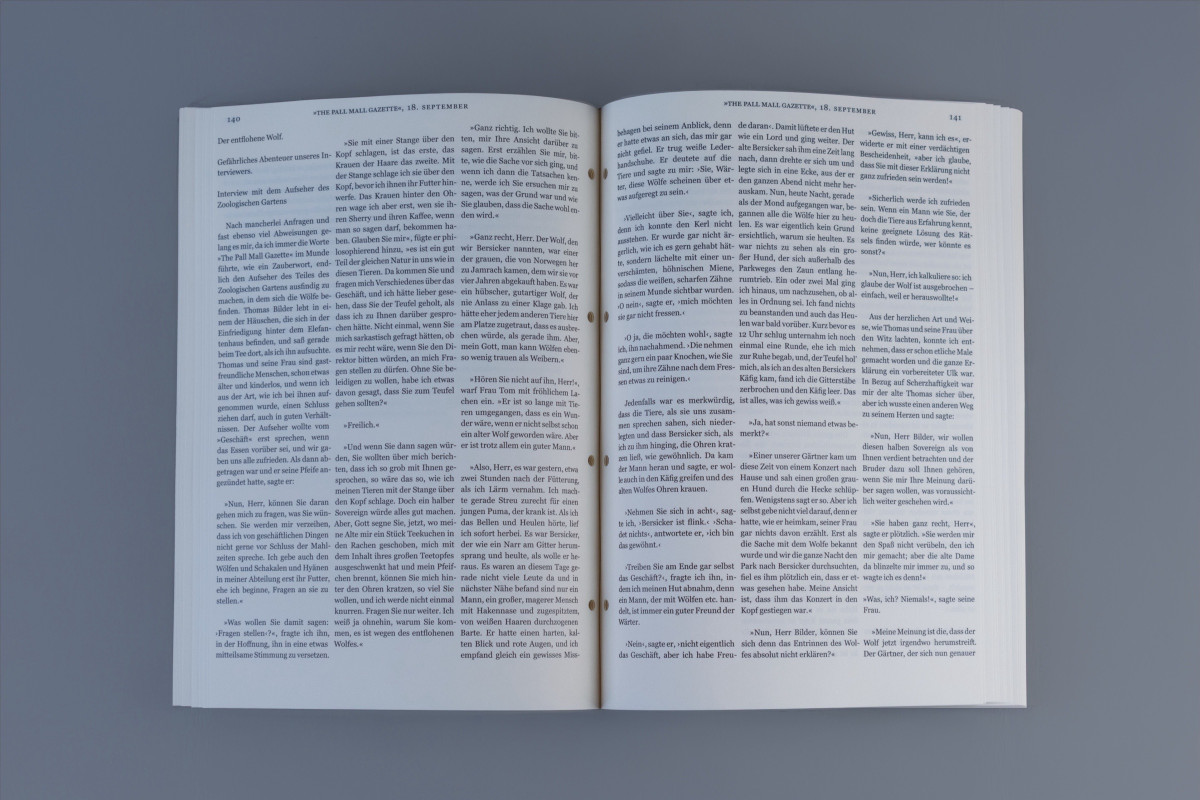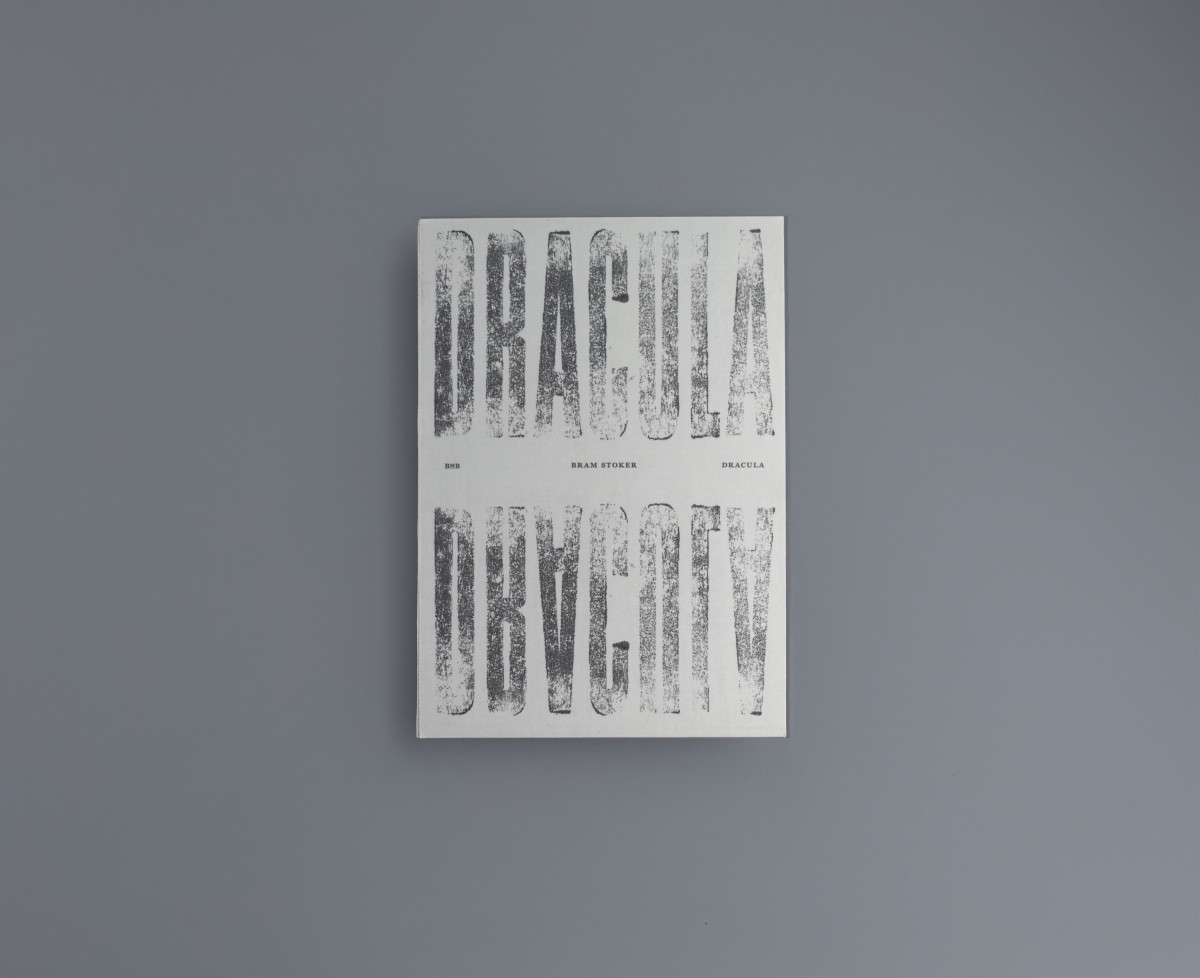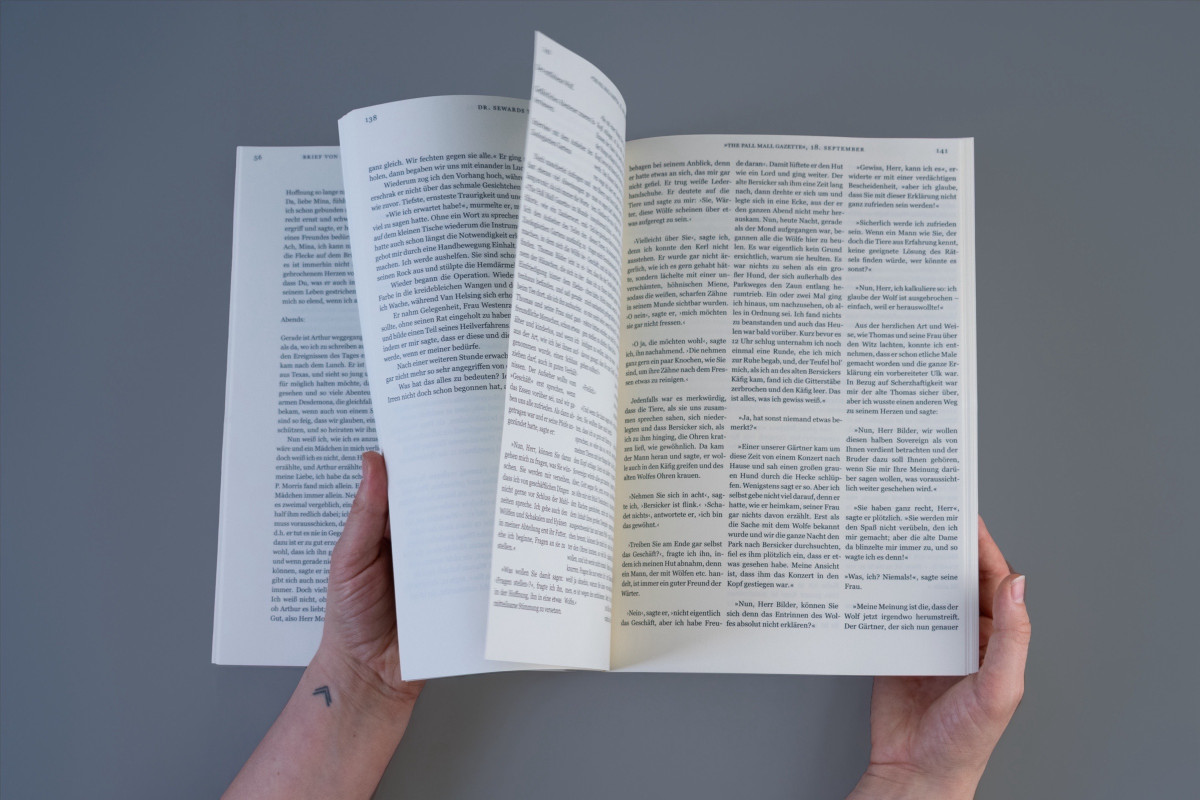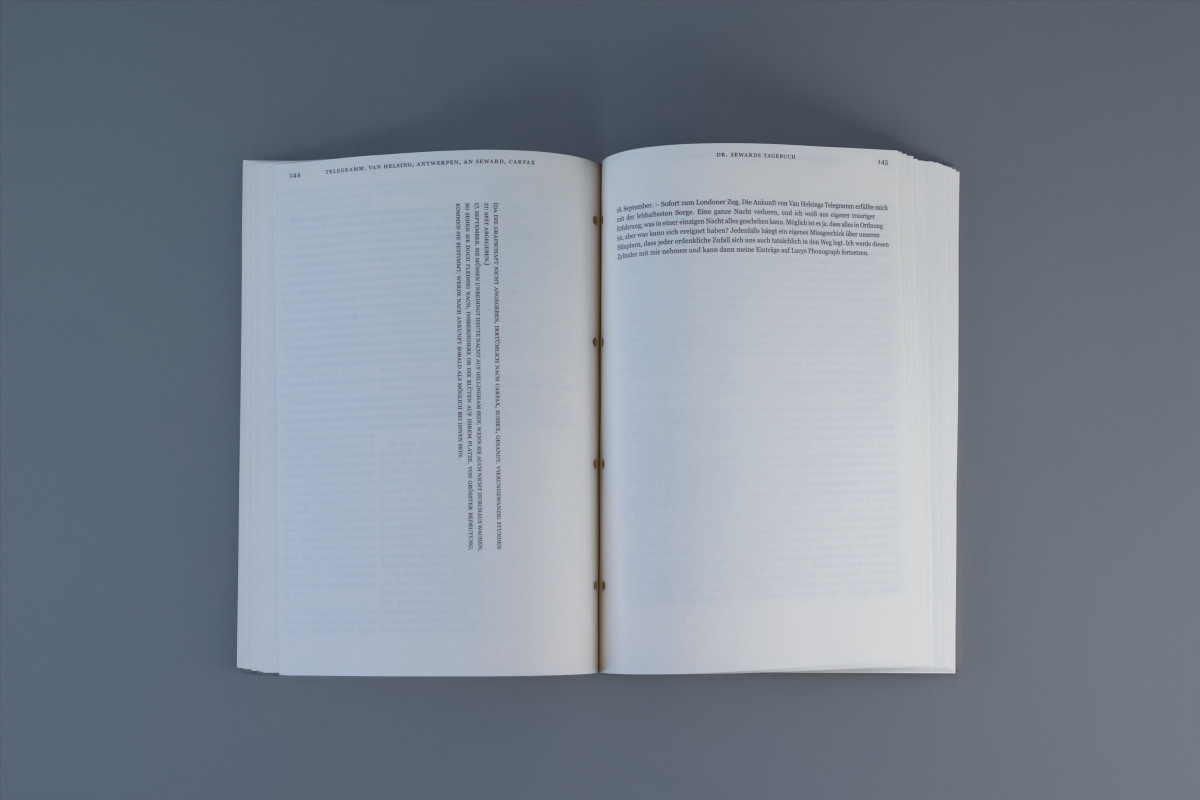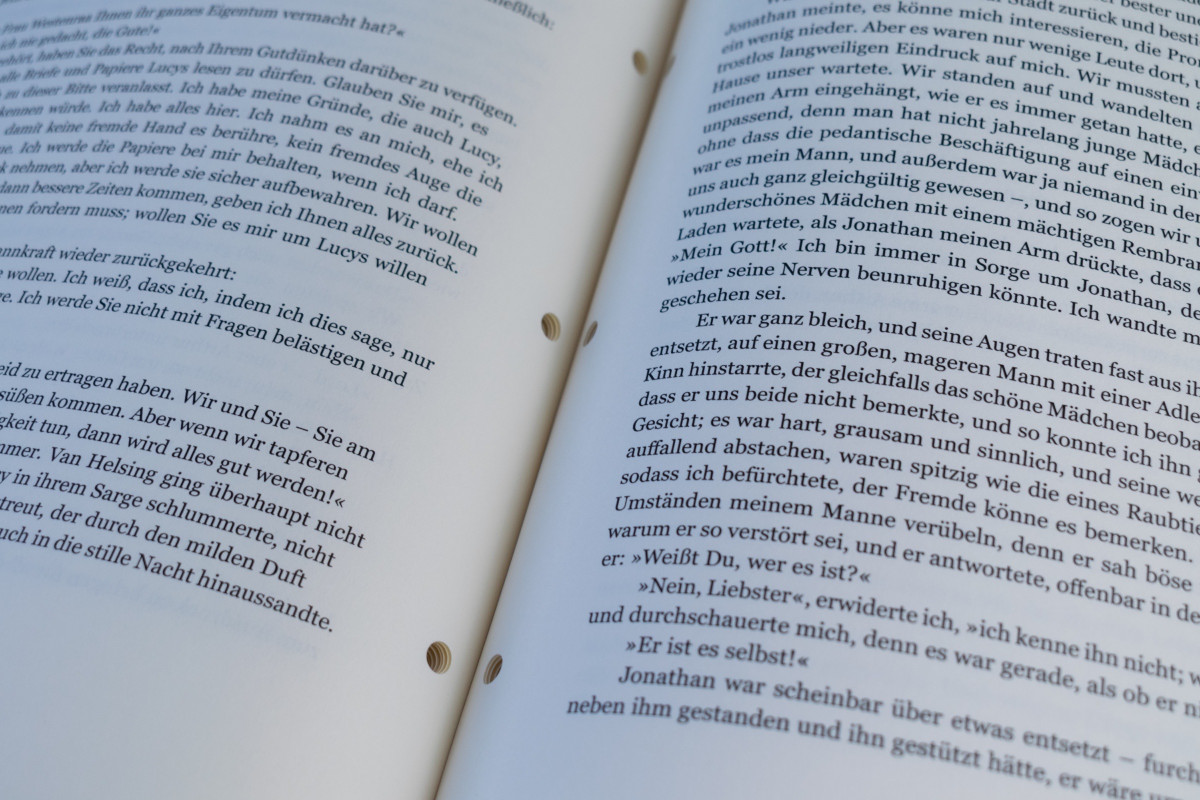
Mein Projekt „Dracula“ ist eine Buchgestaltung aus dem Sommersemester 2024.
Der Roman aus dem Jahr 1897 ist im epistolaren Stil geschrieben und besteht aus Tagebucheinträgen, Briefen, Zeitungsartikeln und anderen Dokumenten, die die Geschichte aus verschiedenen Perspektiven erzählen. Dieser Erzählstil ermöglicht es den Lesern, die Gedanken und Gefühle der Charaktere direkt mitzuerleben und schafft eine intime Verbindung zur Handlung.
Das Ergebnis meiner Arbeit war ein DIN-A4-großes Buch, das den Charakter einer Dokumentensammlung aufgreift. Ich entwickelte vier verschiedene Layouts für die unterschiedlichen Textarten, um den epistolaren Stil zu betonen. Die Dokumente wurden am Kopf des Buches bezeichnet und im Innenteil gelocht, was den Eindruck einer archivierten Akte erzeugt. Das Cover wurde mit silbernem Leinen bezogen und mit handgedruckten Bleisatzbuchstaben digital bedruckt. Das Buch erhielt einen offenen Rücken und eine Klebebindung.
My „Dracula“ project was a book design in which I reimagined Bram Stoker‘s novel.
The novel is written in epistolary style and consists of diary entries, letters, newspaper articles, and other documents that tell the story from various perspectives. This narrative style allows readers to directly experience the thoughts and feelings of the characters and creates an intimate connection to the plot.
The result of my work was an A4-sized book that captures the character of a document collection. I developed four different layouts for the various types of text to emphasize the epistolary style. The documents were labeled at the head of the book and hole-punched in the interior, creating the impression of an archived file. The cover was bound in silver linen and digitally printed with hand-pressed letterpress type. The book received an exposed spine and perfect binding. The project began in April 2024 and was completed in December 2024.